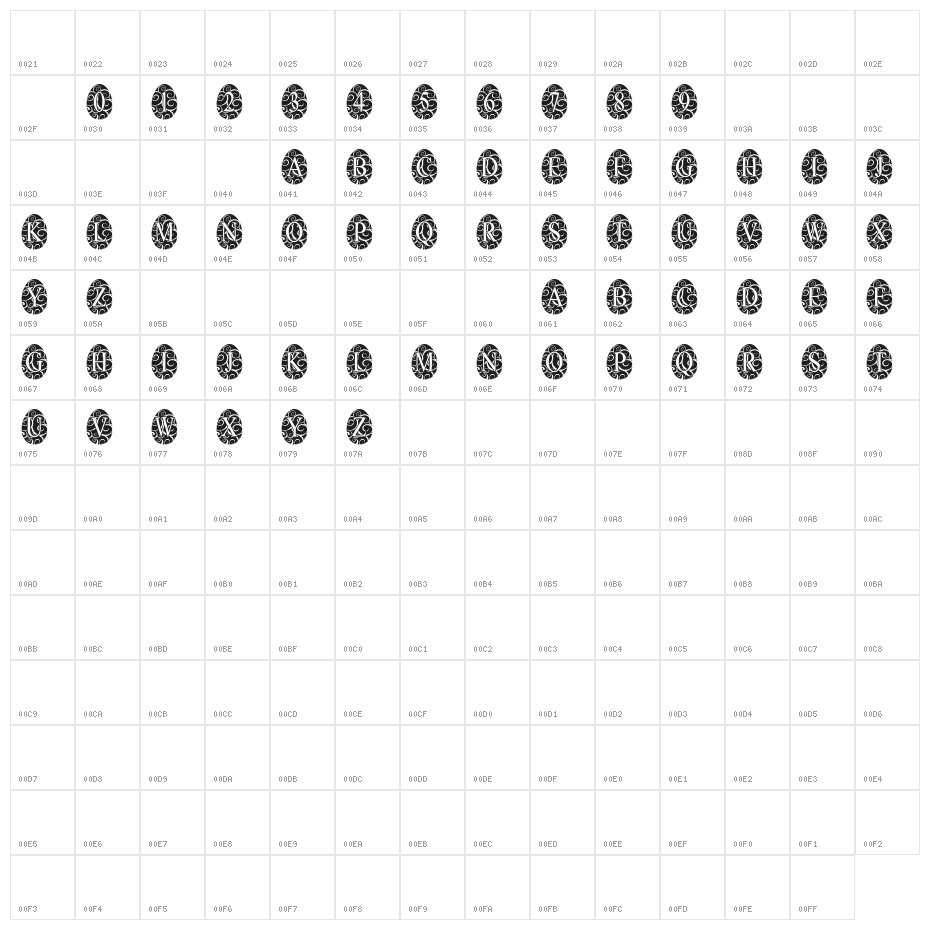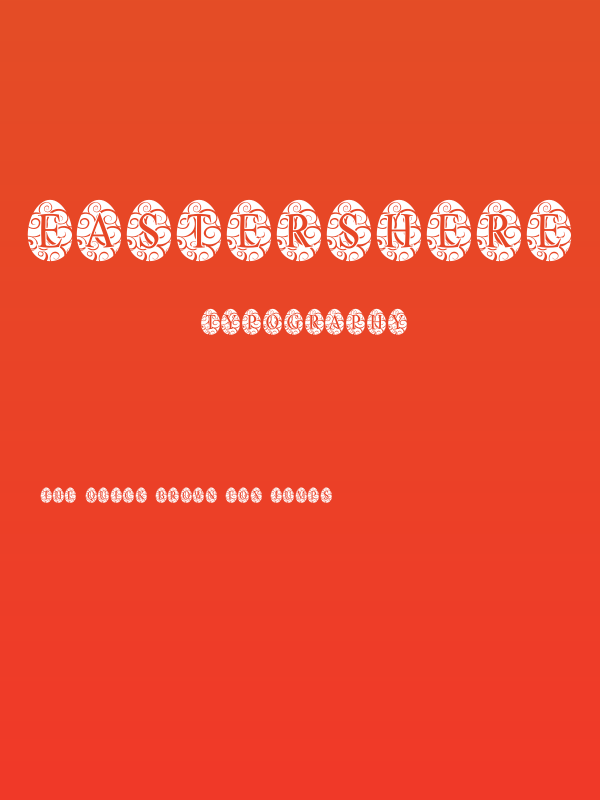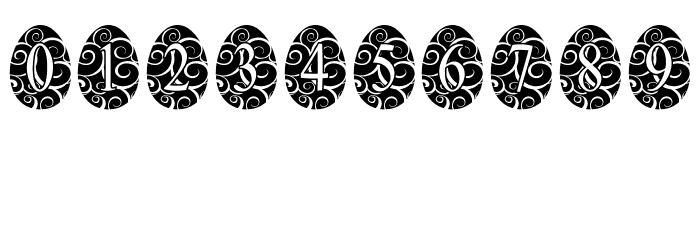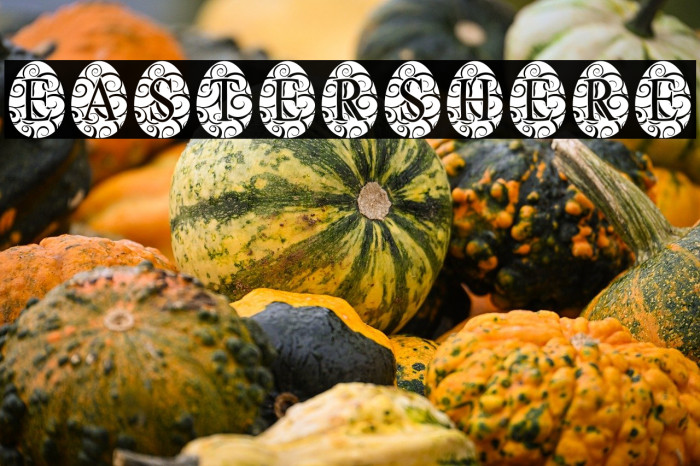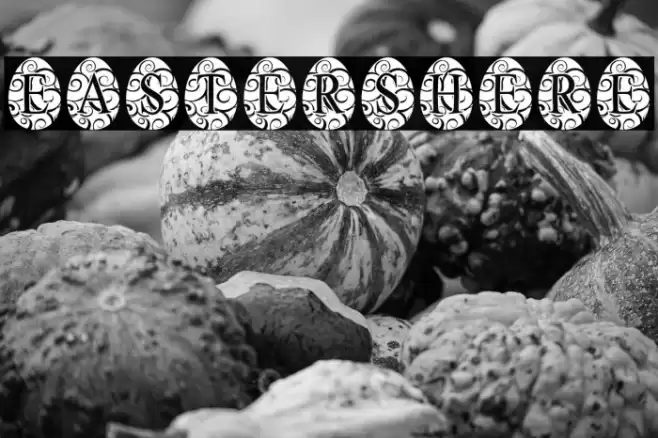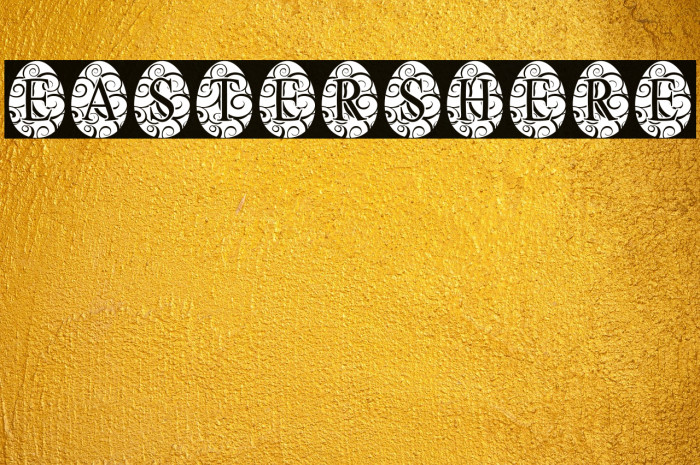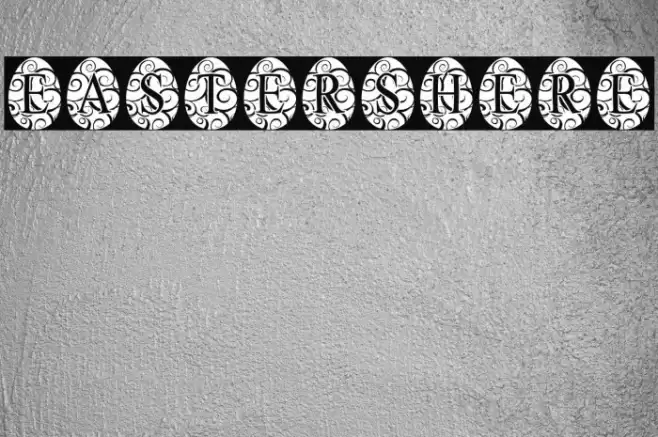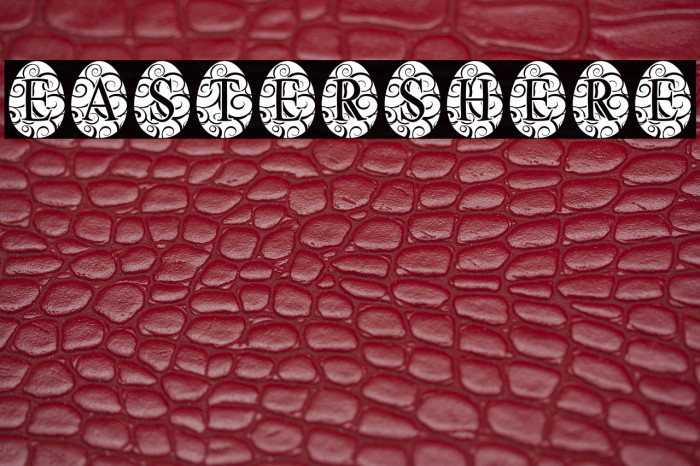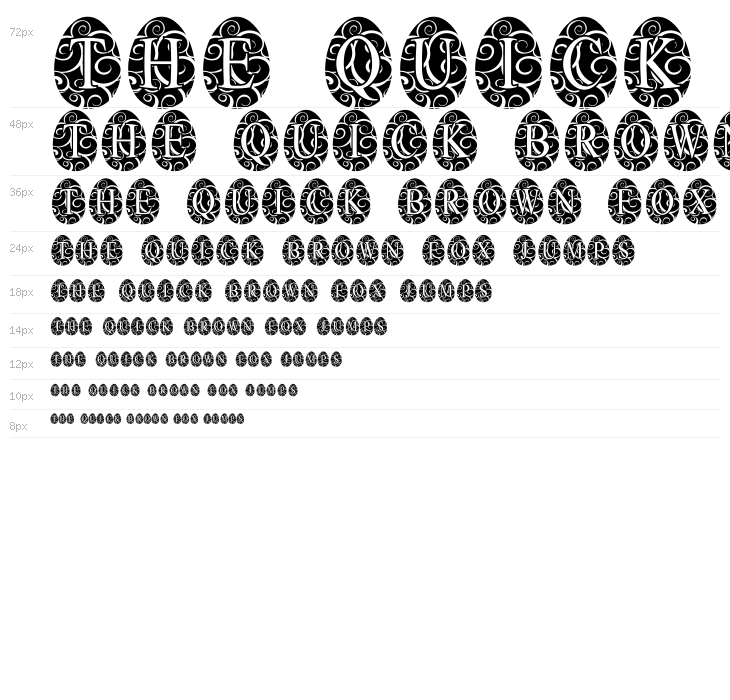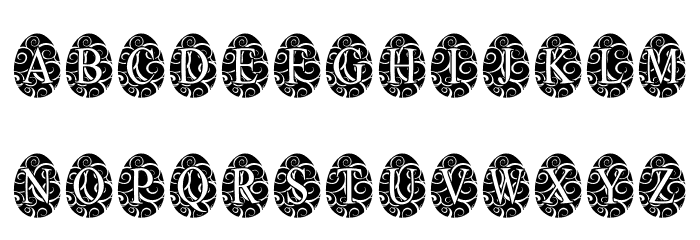
Easters_Here Font
✎ Easter
| Categorii | Easter |
| Caz de utilizare | Headlines, Logos, Invitations |
| Proiecte propuse | Ideal for Easter-themed designs, greeting cards, festive banners, and invitations. |